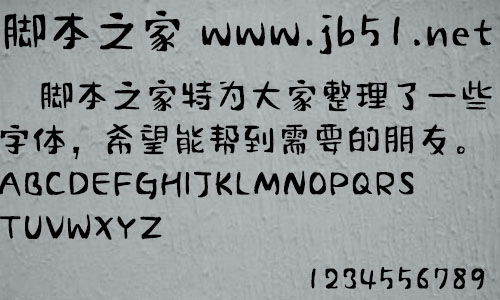
漢儀二碼涂鴉W一款不錯(cuò)的藝術(shù)字體,由漢儀字庫出品,字體筆觸粗實(shí),字形端正,具有很好的視覺感,適合應(yīng)用于藝術(shù)設(shè)計(jì)、平面宣傳設(shè)計(jì)、網(wǎng)頁設(shè)計(jì),書法字帖等領(lǐng)域,需要的朋友可以前來本站下載。